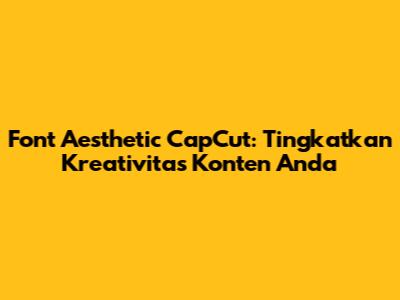
Font aesthetic CapCut merupakan elemen krusial dalam menciptakan konten video yang menarik dan memukau. Pemilihan font yang tepat dapat memberikan kesan visual yang kuat, menyampaikan pesan dengan lebih efektif, dan meningkatkan engagement penonton. Bagi para kreator konten, baik pemula maupun profesional, memahami rekomendasi font aesthetic CapCut adalah kunci untuk menghasilkan video yang tidak hanya informatif tetapi juga estetis. Dalam artikel ini, kita akan membahas secara mendalam berbagai jenis font aesthetic yang bisa Anda gunakan di CapCut, tips memilih font yang sesuai dengan tema video, dan bagaimana cara mengaplikasikannya.
Memilih font aesthetic yang tepat di CapCut bisa jadi tantangan tersendiri, guys. Ada begitu banyak pilihan, mulai dari yang klasik hingga modern, dari yang formal hingga playful. Namun, jangan khawatir! Artikel ini akan membantu Anda menavigasi dunia font CapCut dengan mudah. Kita akan mulai dengan mengenal berbagai jenis font yang populer, lalu membahas bagaimana menyesuaikan font dengan tema video Anda. Dengan pengetahuan ini, Anda akan dapat menciptakan video yang tidak hanya informatif tetapi juga memukau secara visual. Jadi, siap untuk meningkatkan kualitas konten video Anda?
Jenis-Jenis Font Aesthetic CapCut yang Wajib Dicoba
Mari kita mulai dengan mengulas beberapa jenis font aesthetic CapCut yang sangat direkomendasikan untuk mempercantik video Anda. Setiap jenis font memiliki karakteristik unik yang dapat disesuaikan dengan kebutuhan konten Anda. Dengan memahami perbedaan ini, Anda dapat memilih font yang paling cocok untuk menyampaikan pesan dan meningkatkan daya tarik visual video Anda. Yuk, simak beberapa rekomendasi berikut:
1. Font Serif: Klasik dan Elegan
Font serif adalah jenis font yang memiliki serif, atau garis kecil pada ujung huruf. Font ini seringkali memberikan kesan klasik, elegan, dan formal. Cocok untuk video yang ingin menyampaikan kesan profesionalisme atau keanggunan. Beberapa contoh font serif yang populer di CapCut antara lain Times New Roman, Georgia, dan Playfair Display. Font serif sangat ideal digunakan untuk judul video, subtitle, atau teks yang membutuhkan kesan serius dan berkelas. Penggunaan font ini akan memberikan look yang timeless dan sophisticated pada video Anda. Jangan ragu untuk mencoba font serif jika Anda ingin menciptakan kesan yang classy.
2. Font Sans-Serif: Modern dan Mudah Dibaca
Berbeda dengan font serif, font sans-serif tidak memiliki serif pada ujung hurufnya. Font ini cenderung lebih modern, bersih, dan mudah dibaca, bahkan dalam ukuran kecil. Font sans-serif sangat cocok untuk video dengan konten yang membutuhkan kejelasan dan readability tinggi. Beberapa contoh font sans-serif yang populer di CapCut adalah Arial, Helvetica, dan Montserrat. Font sans-serif sangat baik digunakan untuk body text, informasi singkat, atau teks yang perlu mudah dipahami oleh penonton. Jika Anda ingin video Anda terlihat clean dan modern, font sans-serif adalah pilihan yang tepat. Cobalah berbagai variasi font sans-serif untuk menemukan yang paling sesuai dengan gaya visual video Anda.
3. Font Script: Personal dan Artistik
Font script meniru tulisan tangan manusia, memberikan kesan personal, artistik, dan stylish. Font ini sering digunakan untuk video yang ingin menyampaikan kesan personal touch, kreativitas, atau keunikan. Beberapa contoh font script yang populer di CapCut adalah Great Vibes, Dancing Script, dan Allura. Font script cocok untuk quotes, watermark, atau teks yang ingin ditonjolkan sebagai elemen dekoratif. Namun, perlu diingat bahwa font script kadang sulit dibaca dalam ukuran kecil, jadi gunakan dengan bijak dan pertimbangkan readability.
4. Font Display: Menarik Perhatian
Font display adalah jenis font yang dirancang untuk menarik perhatian dengan bentuk huruf yang unik dan eye-catching. Font ini sering digunakan untuk judul, headline, atau teks yang ingin ditonjolkan. Beberapa contoh font display yang populer di CapCut adalah Bebas Neue, Impact, dan Anton. Font display sangat cocok untuk video dengan tema yang bold, funky, atau kreatif. Gunakan font display secara hati-hati agar tidak terkesan berlebihan dan tetap sejalan dengan keseluruhan estetika video.
Tips Memilih Font Aesthetic CapCut yang Sesuai dengan Tema Video
Setelah mengenal berbagai jenis font aesthetic CapCut, langkah selanjutnya adalah memilih font yang sesuai dengan tema video Anda. Pemilihan font yang tepat akan meningkatkan koherensi visual dan memperkuat pesan yang ingin Anda sampaikan. Berikut adalah beberapa tips yang bisa Anda terapkan:
1. Sesuaikan dengan Tema dan Gaya Video
Font aesthetic harus selaras dengan tema dan gaya video Anda. Misalnya, jika Anda membuat video tentang kuliner, font yang fun dan playful mungkin lebih cocok. Jika Anda membuat video bisnis, font yang professional dan elegan akan lebih tepat. Pikirkan tentang suasana yang ingin Anda ciptakan dan pilih font yang mencerminkan suasana tersebut. Pastikan font yang Anda pilih mendukung pesan visual yang ingin Anda sampaikan. Jangan sampai font yang Anda gunakan bertentangan dengan tema video, guys.
2. Perhatikan Readability
Readability atau keterbacaan adalah faktor penting dalam pemilihan font. Pastikan font yang Anda pilih mudah dibaca, bahkan dalam ukuran kecil atau pada layar smartphone. Hindari font yang terlalu rumit atau dekoratif jika teks yang ditampilkan berukuran kecil atau jika video memiliki banyak elemen visual lain. Font sans-serif biasanya lebih mudah dibaca daripada font serif, terutama dalam ukuran kecil. Selalu uji coba font yang Anda pilih untuk memastikan _readability_nya.
3. Perhatikan Kontras
Kontras antara teks dan background sangat penting untuk readability. Pastikan warna font yang Anda pilih memiliki kontras yang cukup dengan background video Anda. Jika background video Anda terang, gunakan warna font yang gelap, dan sebaliknya. Hindari penggunaan warna font yang terlalu mirip dengan warna background, karena akan sulit dibaca. Eksperimen dengan berbagai kombinasi warna untuk menemukan yang paling efektif.
4. Gunakan Font yang Konsisten
Konsistensi dalam penggunaan font akan menciptakan tampilan visual yang lebih profesional dan terpadu. Gunakan maksimal dua atau tiga jenis font dalam satu video. Pilih satu font untuk judul, satu font untuk body text, dan mungkin satu font lagi untuk elemen dekoratif. Hindari penggunaan terlalu banyak jenis font, karena dapat membuat video terlihat berantakan dan membingungkan penonton. Konsistensi akan membantu memperkuat branding visual video Anda.
Cara Mengaplikasikan Font Aesthetic di CapCut
Setelah memilih font aesthetic CapCut yang tepat, langkah selanjutnya adalah mengaplikasikannya di aplikasi CapCut. Berikut adalah langkah-langkah mudah untuk melakukannya:
1. Buka Proyek Anda di CapCut
Buka aplikasi CapCut dan mulai proyek baru atau buka proyek yang sudah ada. Pastikan video yang ingin Anda edit sudah ada di timeline.
2. Tambahkan Teks
Ketuk ikon